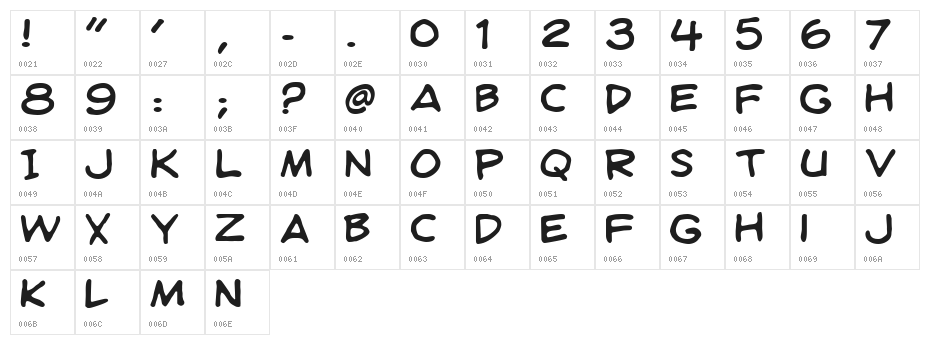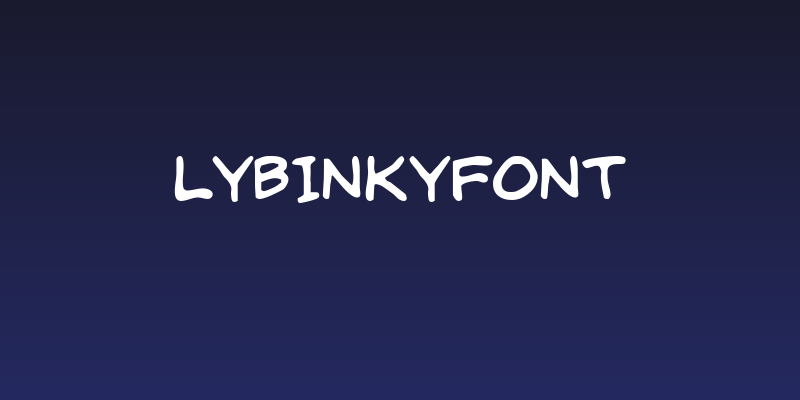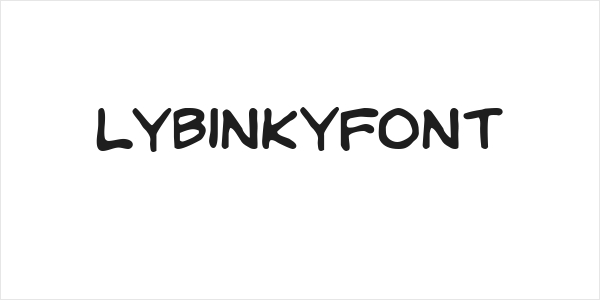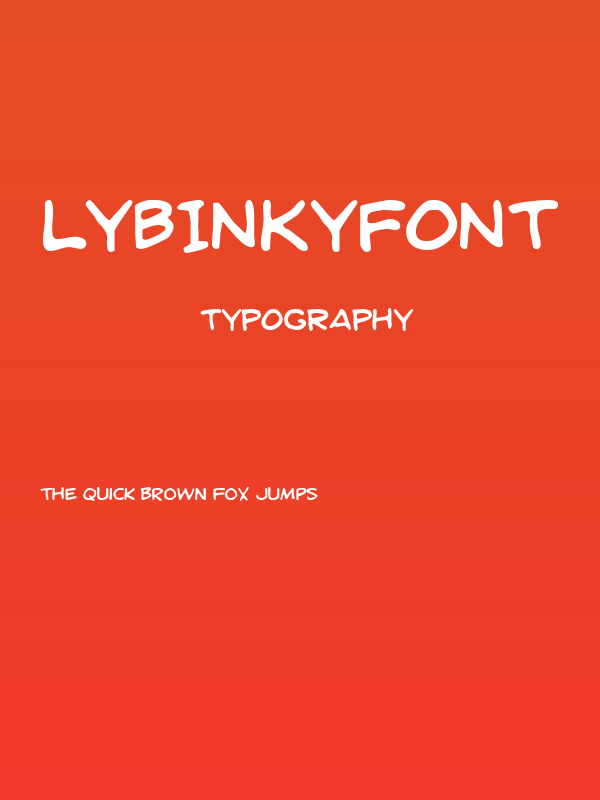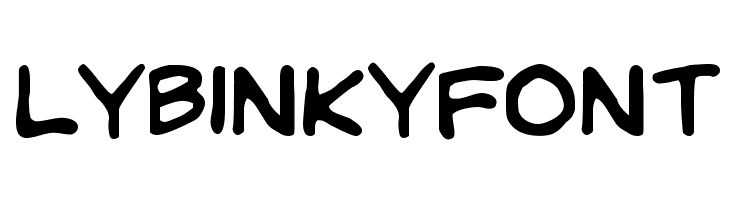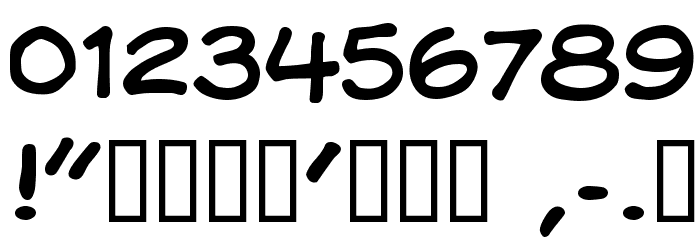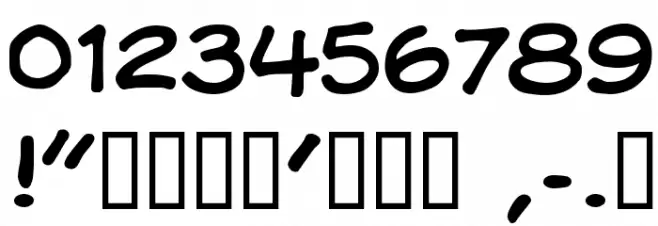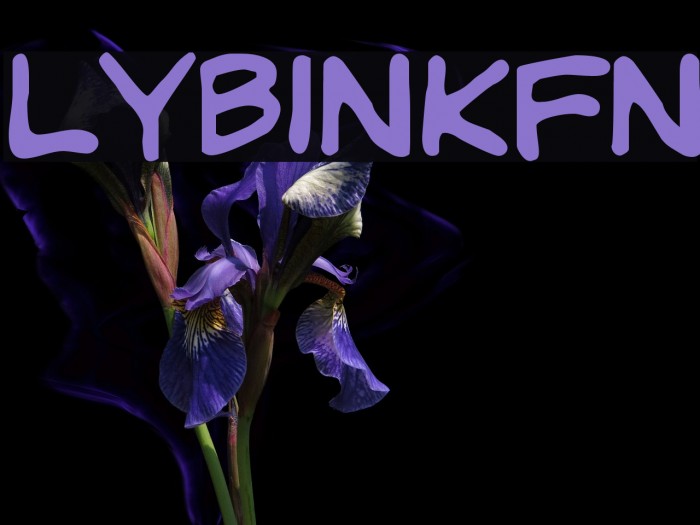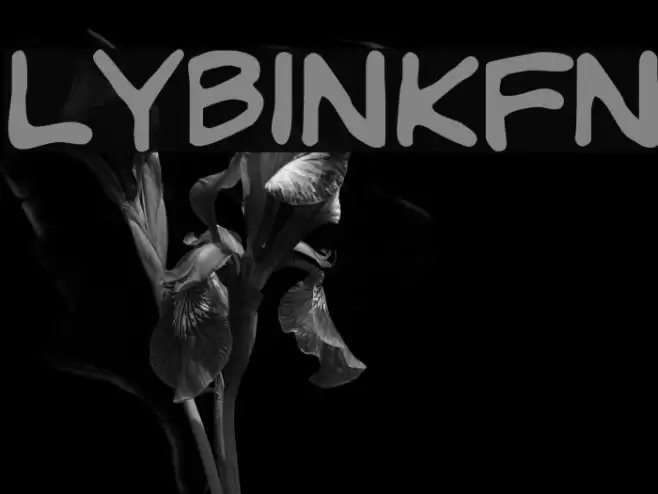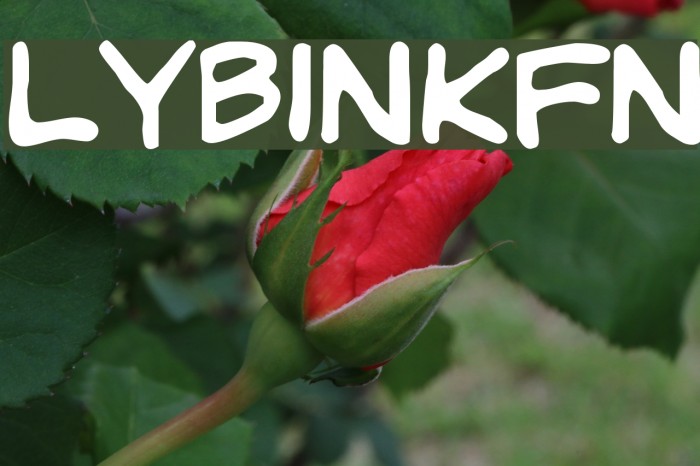
LYBinkyFont Font
| Style général | Playful |
| Cas d'utilisation | Headlines, Logos, Informal text |
| Projets proposés | Children's books, playful branding, casual invitations, greeting cards. |